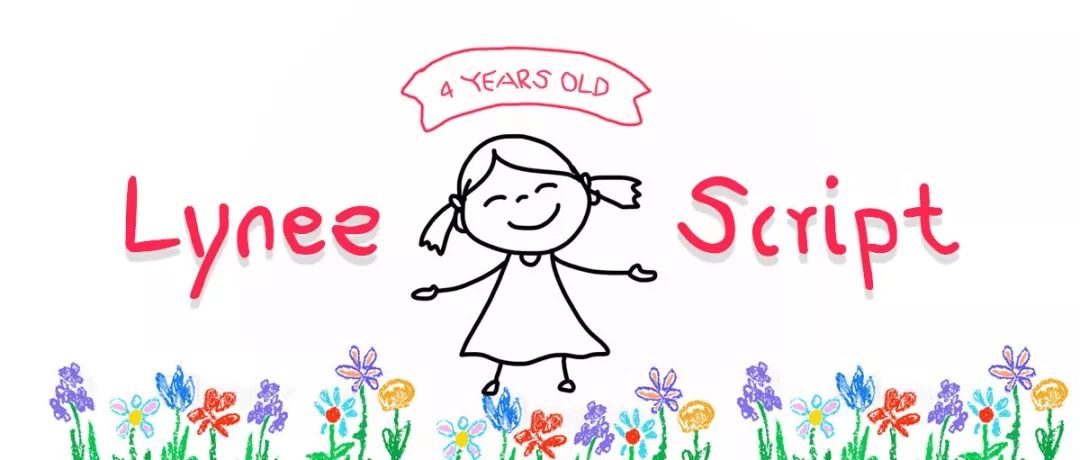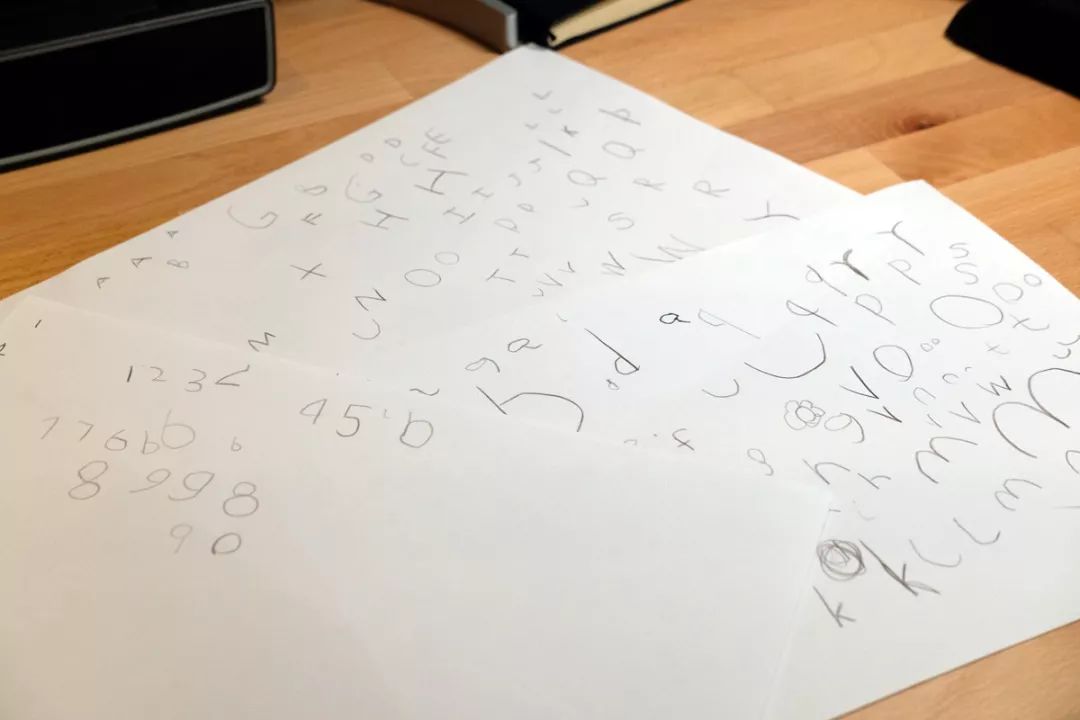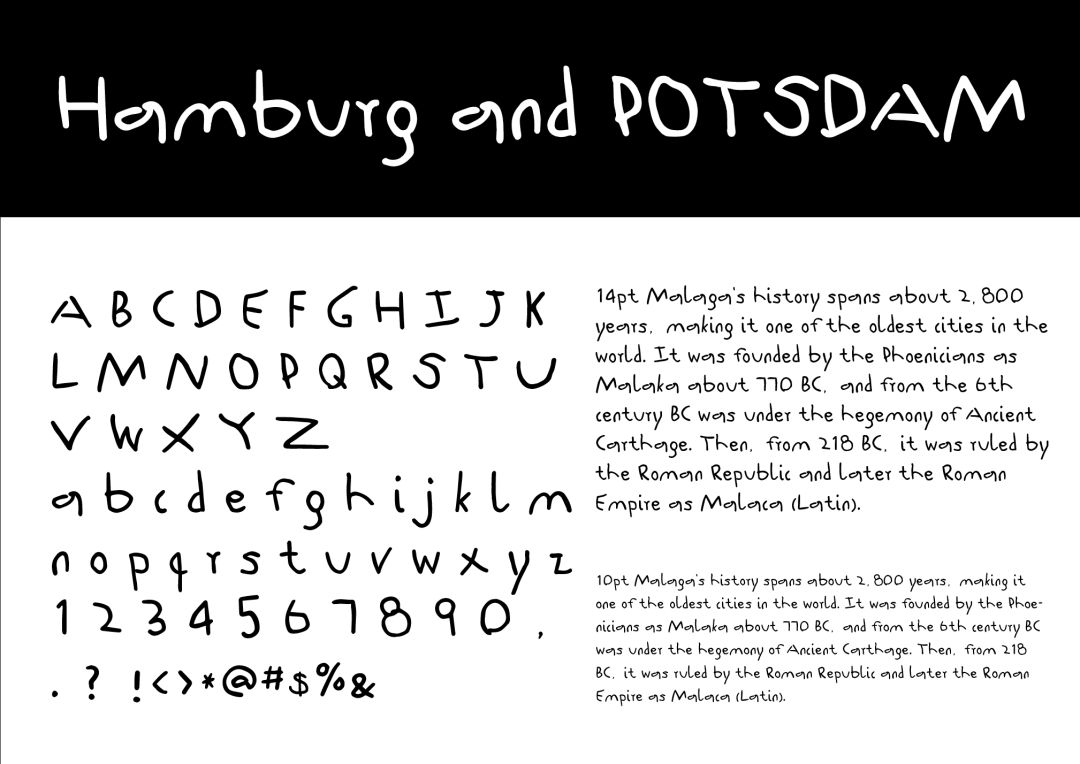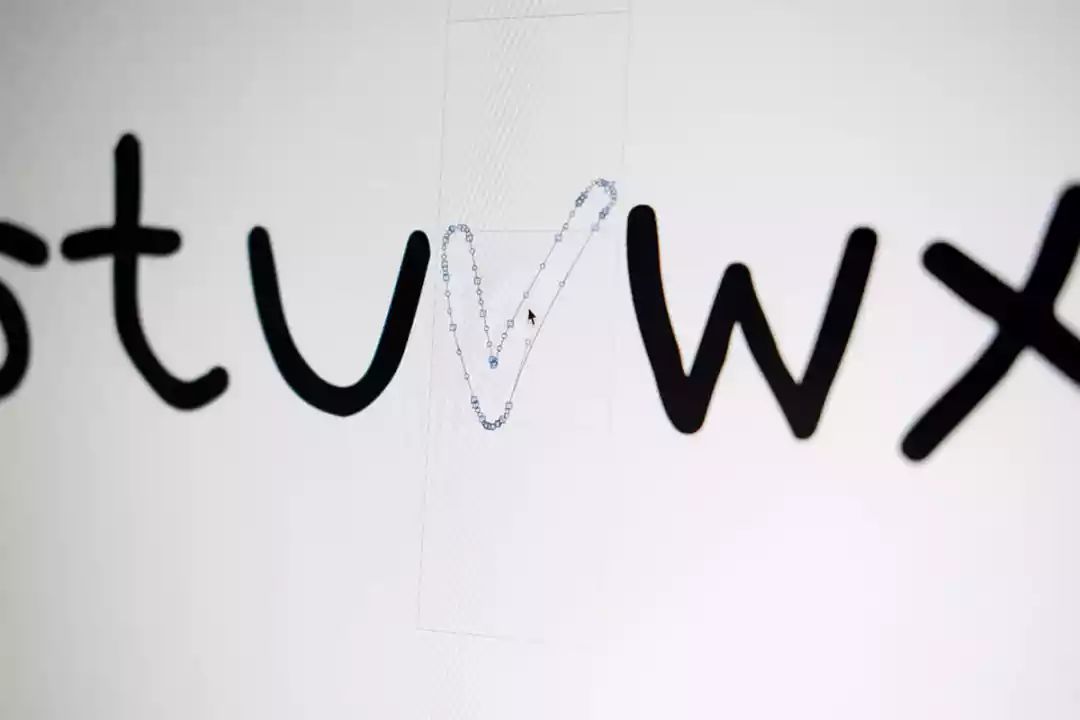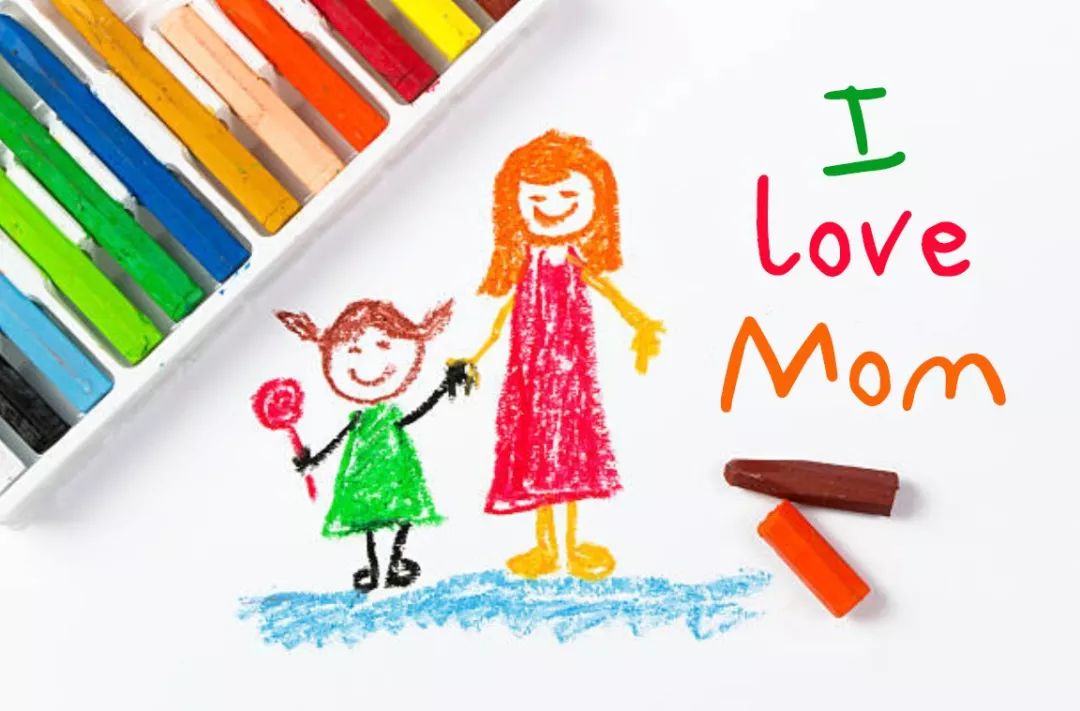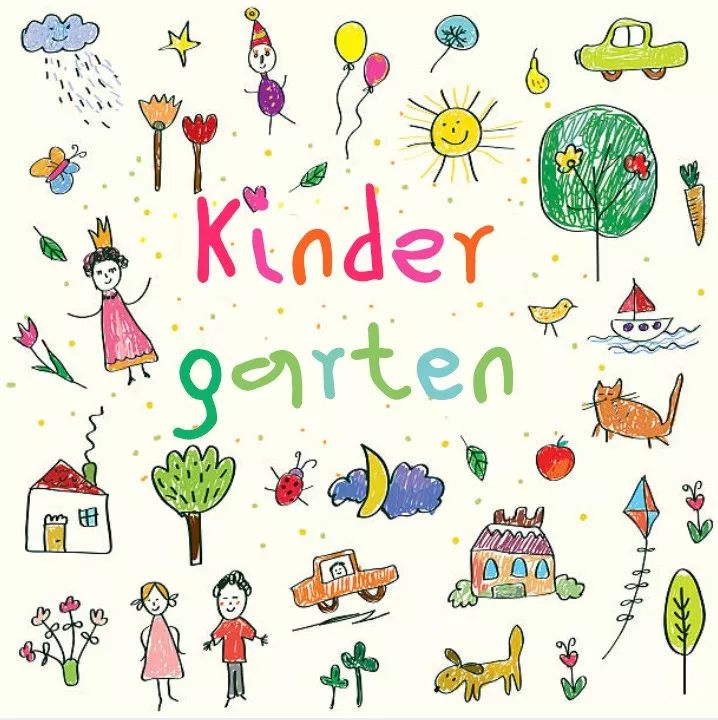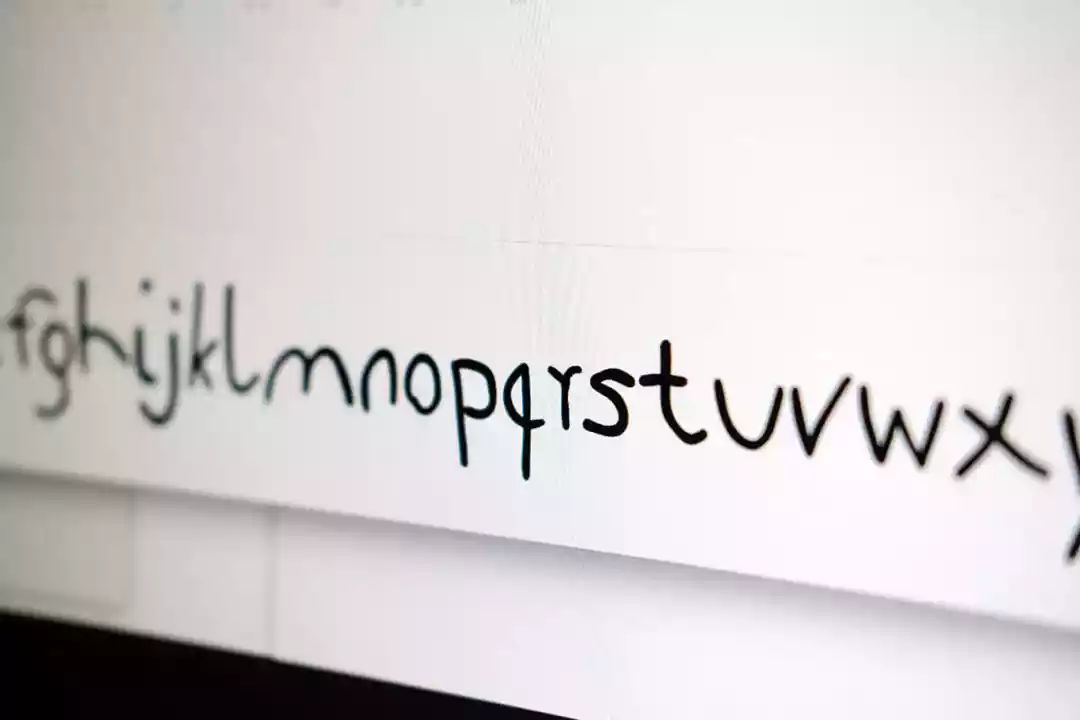
这位暖男爸爸,为 4 岁的女儿制作了一款专属字体!
{{tag.name}}小编近日刷朋友圈,发现 TypeSchool 学员——同时也是一位非常厉害的设计师——Jeii 的一篇文章刷了屏。点进去一看,原来是他用 TypeSchool 所学的技能,将女儿 Lynee 的手写字做成了字体!下面,就听听这位「女儿奴」亲口来讲讲,小公主的这款字体是怎样诞生的——
家里有个宝贝女儿,自打生出来就想着法子陪她玩。
记得她 6 个月的时候,我就动用高科技陪她认识水果了。之后学会了画画更是不得了:家里 1 米以下的墙上,门上都满是她超现实主义与抽象主义的画作。
而在接触了英文之后,小令仪也会慢慢的写一些不着边际的英文字母了:
于是我冒出了一个想法:
如果她可以完整的写出 26 + 26 个大小写字母,再加上数字以及一些标点符号,那我们就来共同做一款字体吧!
手稿
想要一个熊孩子把 26 大写 + 26 小写 + 10 个数字以及常用符号写出来,那是要做思想工作的。在各种坑蒙拐骗之后,得到了以下珍贵的手稿。
(每个字母都需要多写几遍,这在之后会解释)
整理手稿
接下来需要把手稿扫描进电脑里,在不改变比例的情况下,调整大小和排列整齐,等待下一步数位复刻。
(小写字母d 的选取和整理)
(大写字母S, U, V, W的整理,对,T一开始漏了)
数位复刻
接下来该是 iPad 出场了。
把整理好的手写稿以 jpg 的方式 Airdrop 给 iPad, 并在 Procreate APP 里打开,设置一个 50% 的透明度,用 Apple Pencil 描红。我选用了一个略带笔触的画笔。
字体制作
到了这一步便开始专业了,主要是将复刻手写稿转曲,调整并导入到专业的字体设计软件 Glyphs。(这是一款专业的字体设计软件,目前只有 MacOS 平台上有)
因为去年参加了 3type(三言)的西文 TypeSchool,并得到了 Glyphs 开发者,Georg 为期一周的指点,功力大增。
当然,字体的调整制作的过程是痛苦的,字间距和字偶距可以把人逼疯。
每每要到疯的边缘的时候,就想想宝贝女儿在家说「爸爸是臭鼬」,嘴角泛起一丝围笑,也就咬牙继续调整下去了。
当当当挡!
接下来让我隆重介绍这款 令仪手写体 Lynee Script v1.0
字体的特点:
原汁原味的孩子气
这款字体保留了我 4 岁女儿原汁原味的孩子气的书写笔迹,这是成人模仿不来的。
可选字形
手写体的一个很重要的特征就是,当一个单词或一句话出现相同字母的时候,人是无法写出一模一样的字来的。所以这款字体在相同字体出现时,可以选择不同的手写字母来还原这种特性。目前大部分小写字母都有两种写法。(未来持续完善)
注意 Look 里的两个 o 是不一样的(辛苦女儿了),aa 也是不同的,还有 e
连接字体(连字)
当我们打出 letter 时,t 与 t 会自动被一个互相连接的双 t 代替,来还原手写字体的特征。同样,effect 的两个f也是如此。